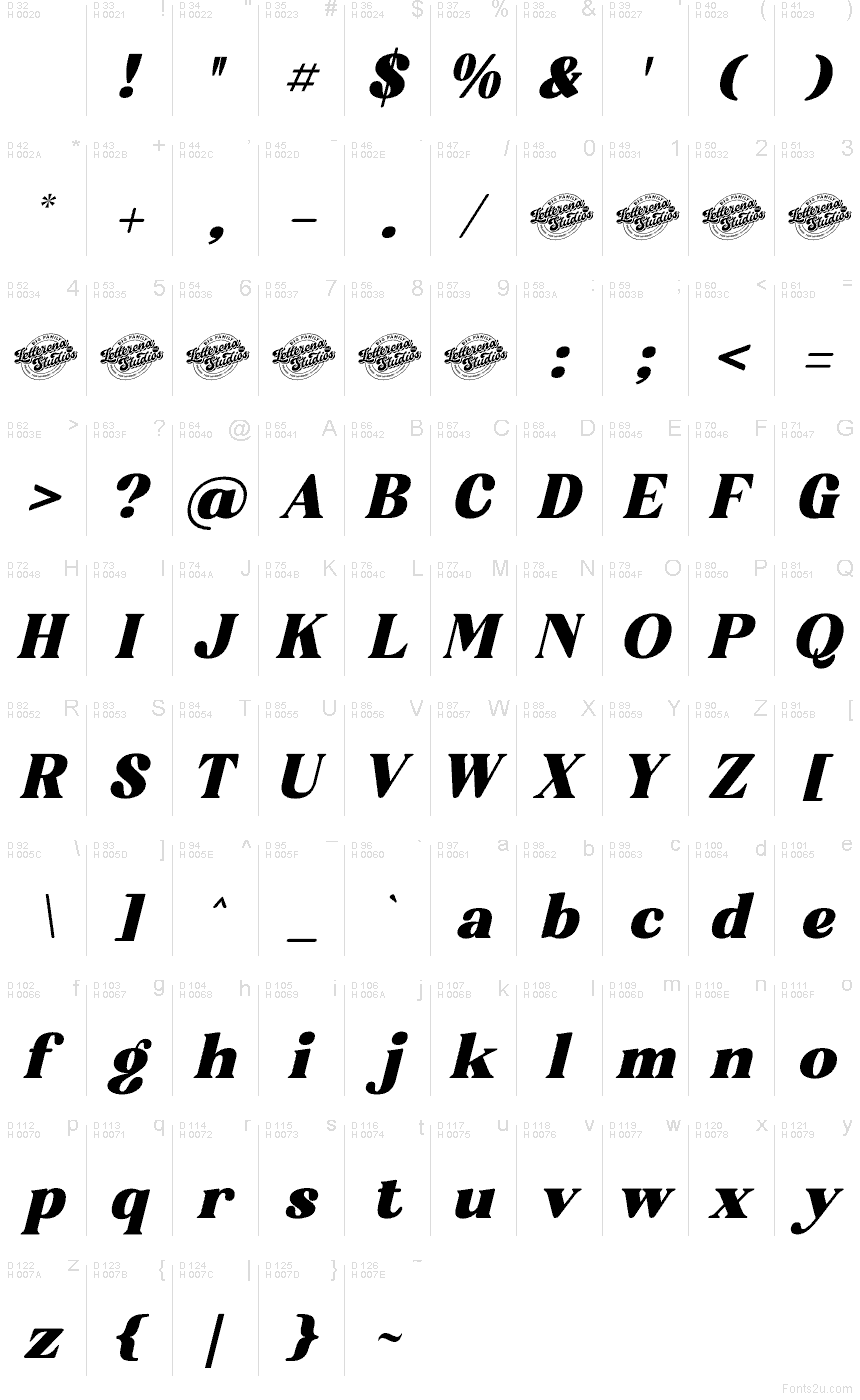
Bright Sunlist Italic da Letterena Studios é uma fonte serifada gratuita e de alto contraste, marcada por uma inclinação expressiva para a frente e uma silhueta distintamente teatral. Curvas largas e escuras encontram junções finíssimas, enquanto as letras justapostas produzem um ritmo denso ao longo da linha de texto.
Ela transita com facilidade entre editoriais de moda e cartazes de espetáculos musicais, já que suas variações marcantes de espessura e seu porte inclinado se adequam tanto à elegância quanto ao impacto visual. Embalagens de luxo representam outro contexto ideal, sobretudo para marcas de perfumes ou doces refinados. Na comunicação visual de eventos, o letreiramento pode atuar quase como uma forma fotográfica recortada e ousada, integrando suas amplas curvas à imagem em volta.